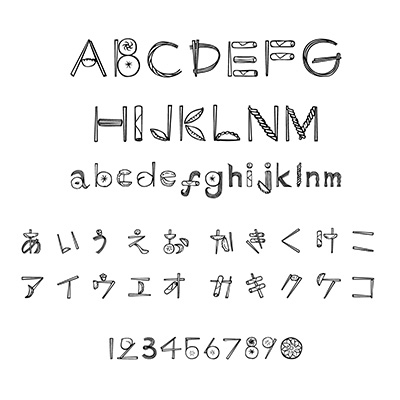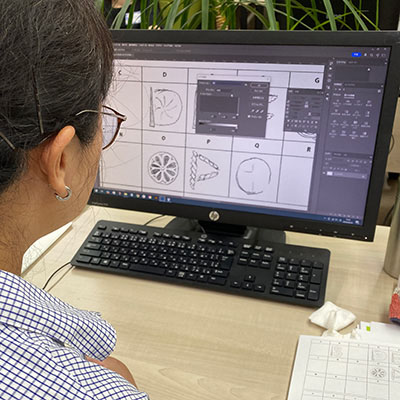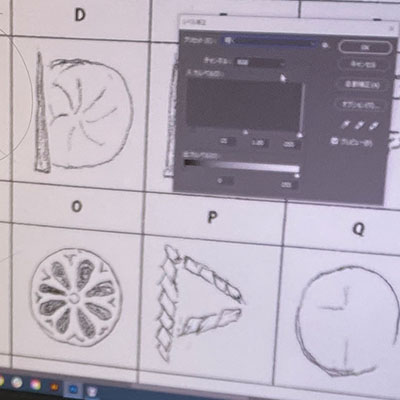
ヨコハマチュウカガイフォント
みんな大好き!横浜中華街フォント
Artist横中愛華
DesignerKozuka.
Organization就労継続支援事業所TED
餃子、麺、お箸などを仮名、欧文に、点心、中華菓子、提灯などを絵文字でつくりました。(横中愛華)
欧文、仮名はまさに「中華!」な食べ物飲み物をアレンジし、おいしい、楽しいデザインをフォントにしました。タイトルや見出しなどにおすすめです。(Kozuka.)
四千年の歴史を凝縮するかのように、こまかなところまでじっくり作り込みました。ひと捻りもふた捻りもあるフォントの細部をお楽しみください。(就労継続支援事業所TED)